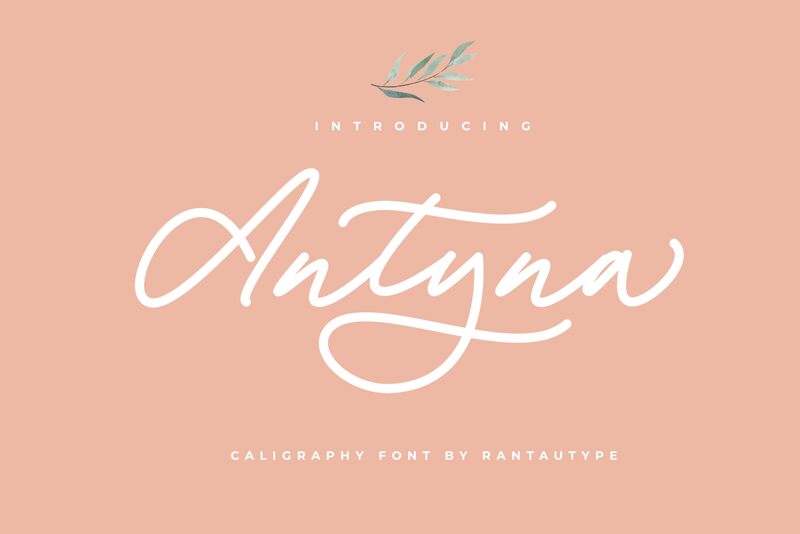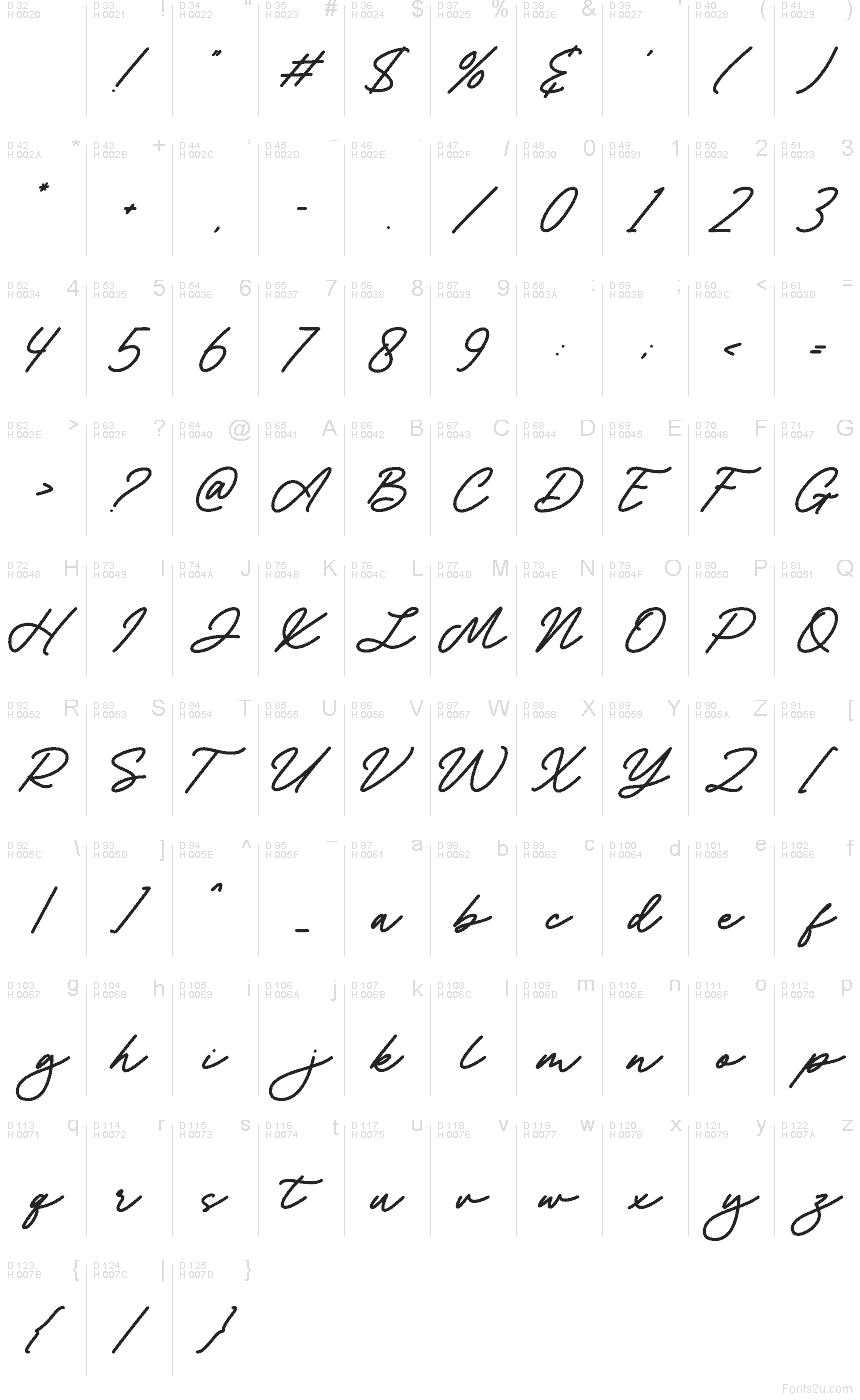
Antyna od RantauType je bezplatné ručně psané skriptové písmo s uvolněným rytmem moderního podpisu. Písmena do sebe plynule zapadají díky dlouhým tahům, širokým oválným smyčkám a lehkému sklonu, který působí osobně a neformálně.
Skvěle se hodí pro branding, obaly kosmetiky, loga butiků, příspěvky na sociální sítě a pozvánky, kde potřebujete, aby jméno nebo krátký text působil jako vlastnoruční podpis. Antyna je bezplatný font, který skvěle vynikne i na obálkách a titulcích, protože díky prodlouženým tahům dodává i krátkým slovům elegantní, ručně kreslený vzhled.